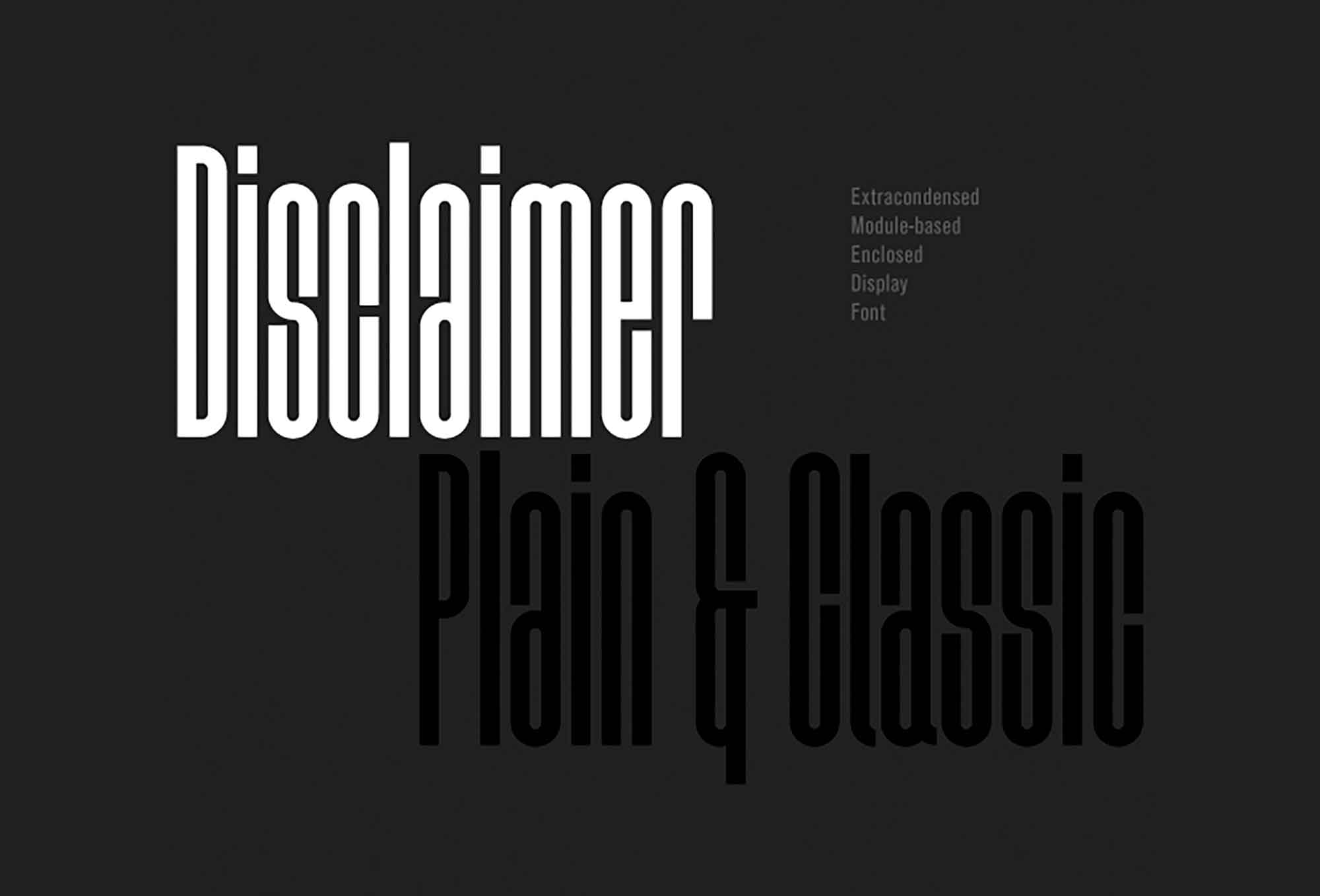
Aqui está uma descrição em português para a página de download do recurso gráfico ‘Disclaimer Condensed Display Font’, com foco em seu uso e beleza: Aviso é uma declaração que nega algo e geralmente não é fixa. Mas é uma certeza que hoje o Aviso nega o esterco de monotonia e aborrecimento. O Aviso vem em duas variações, ambas de que podem ser baixadas gratuitamente. Uma variação de estilo puro, com designs simples que se encaixam bem com cartões de visita, folders, citações e outros materiais. E uma variação clássica, com características mais interessantes, incluindo a colocação única das letras no nível de fundo e ligações com seus apresentações espetaculares. Você também pode usar este recurso para títulos de revistas e livros, design de marca e embalagens, postagens de mídia social, anúncios online e uma variedade de outros projetos, já que o Aviso é uma fonte multilingue. E certifique-se de que tanto o estilo apresenta um conjunto moderno de letras, incluindo letras, números, símbolos e pontuação.